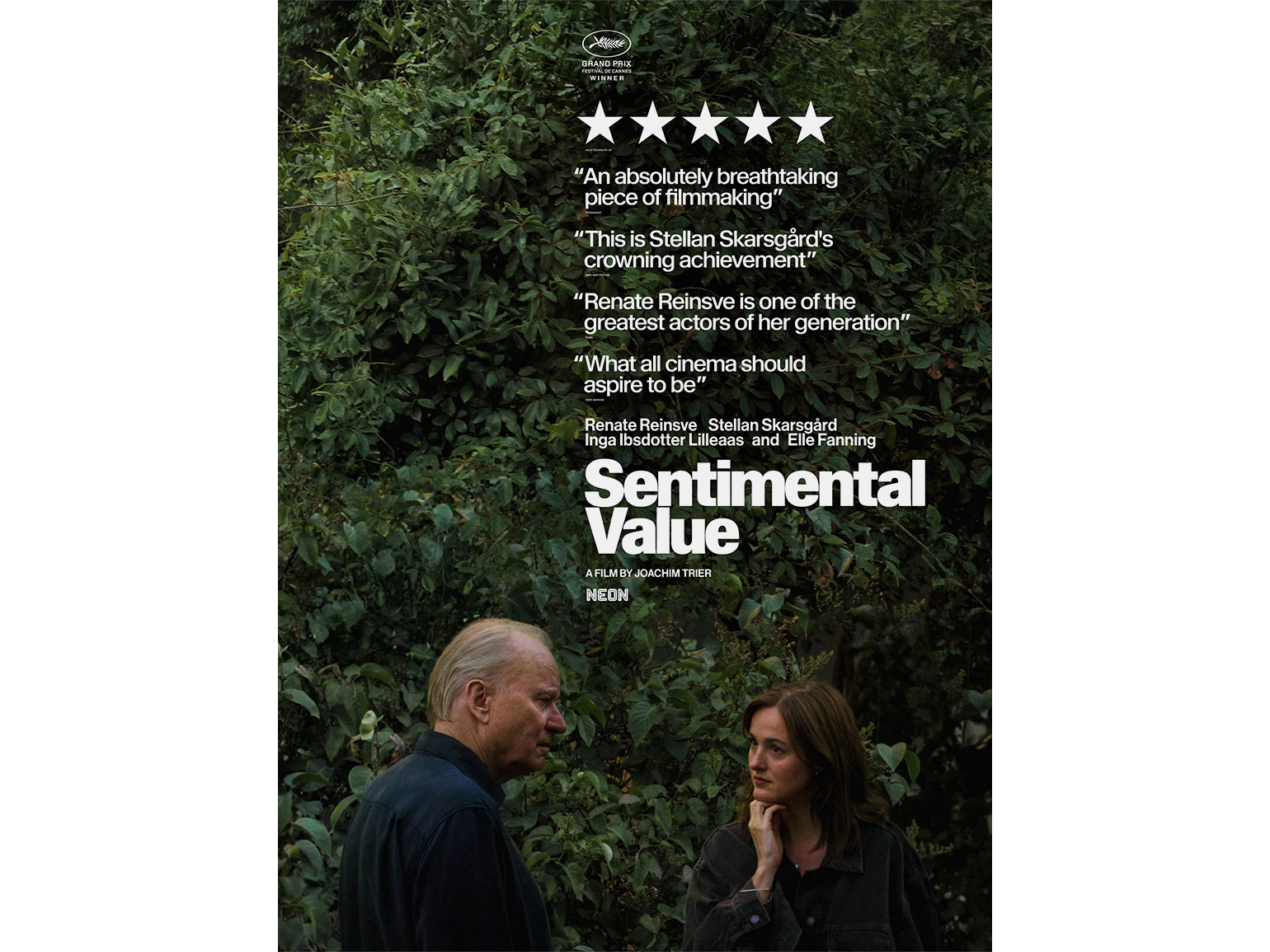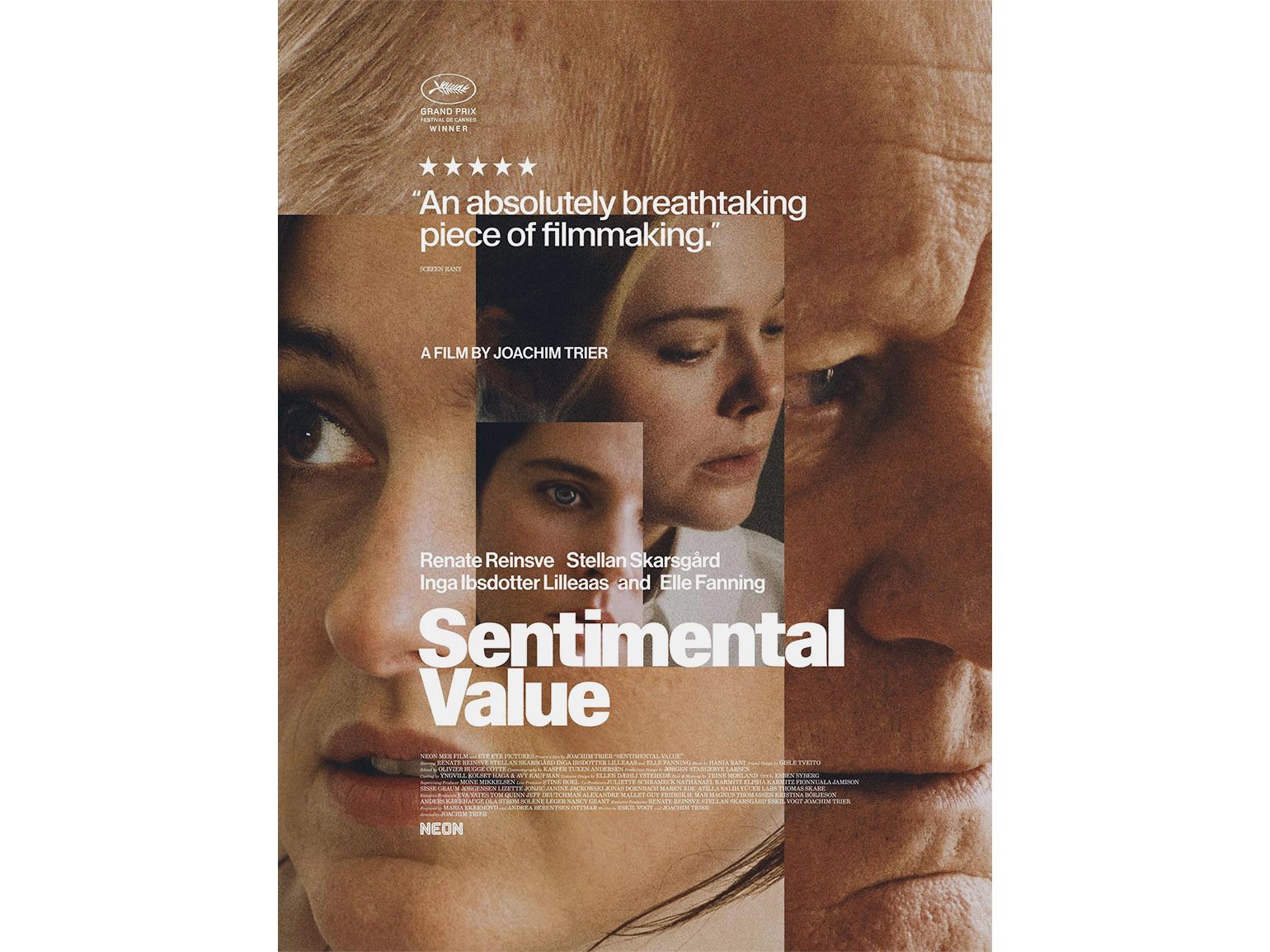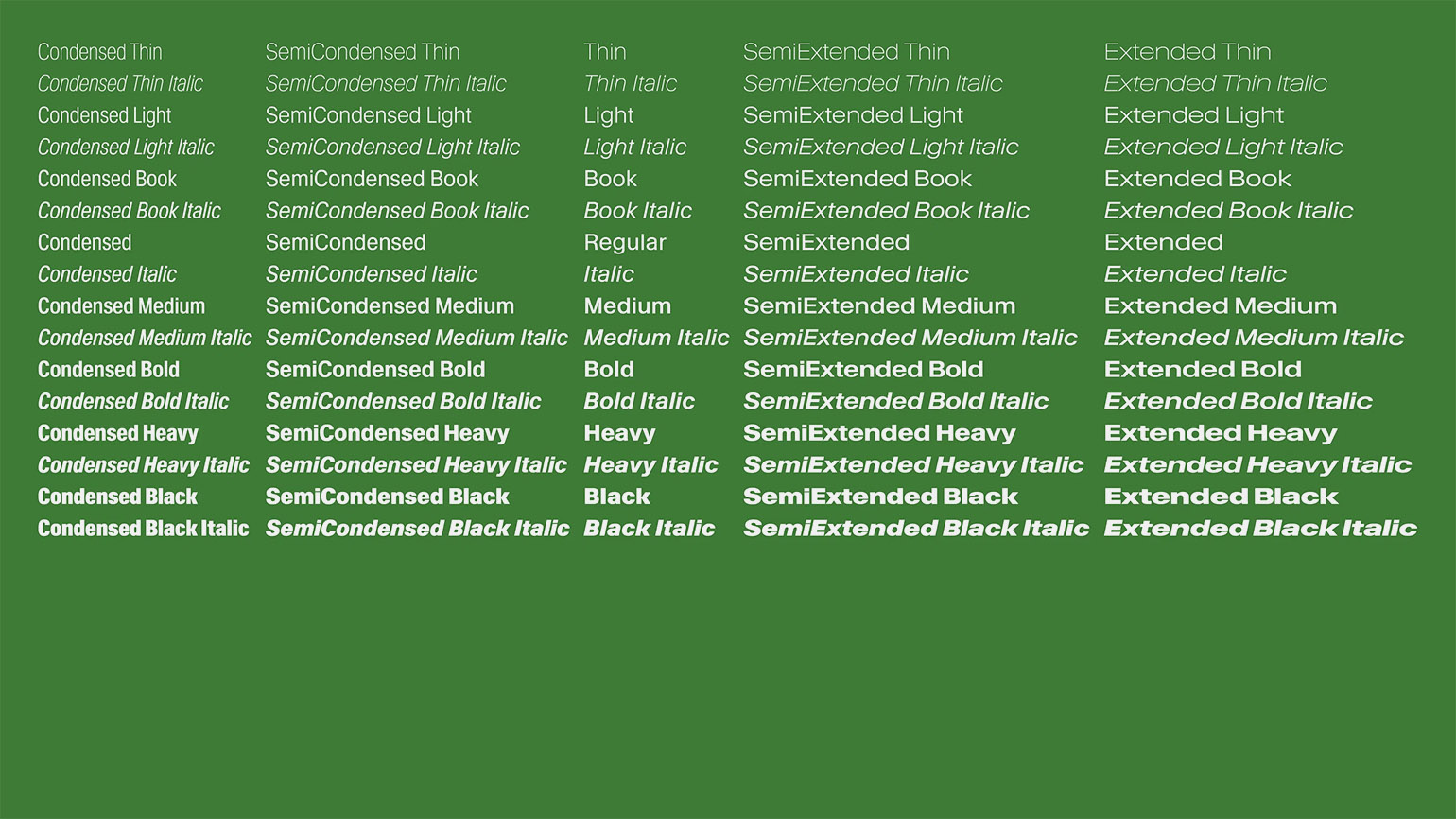
Студия Kimera Foundry разработала шрифт для кампании фильма «Сентиментальная ценность»
Его назвали Waldenburg.
Независимая шрифтовая студия Kimera Foundry стала частью крупного культурного события: её шрифт использовали в визуальной кампании фильма «Сентиментальная ценность», который получил премию «Оскар» в категории «Лучший международный фильм».
Для студии это редкий случай, когда разработанный в независимой среде шрифт Waldenburg выходит за пределы дизайн-контекста и становится элементом массовой культуры. По словам основателя Kimera Майкла Клаузена, такие проекты показывают, как типографика может работать не только как инструмент, но и как часть визуального языка кино.
Waldenburg — один из ключевых проектов студии. Шрифт вдохновлён эстетикой рационализма и одновременно сохраняет гуманистическую выразительность. В его основе лежит баланс между строгой геометрией и «человеческой» пластикой форм, а расширенная гарнитура включает 24 начертания, что делает его универсальным инструментом для разных носителей — от печати до цифровых интерфейсов.
Интерес к шрифту во многом вырос после того, как его использовали в постерах фильма: минималистичная композиция с геометрическим делением пространства и сжатыми формами букв подчеркнула визуальную концепцию картины. В Kimera Foundry отмечают, что для них важно наблюдать, как шрифт выходит за пределы студии и начинает жить в другом контексте.